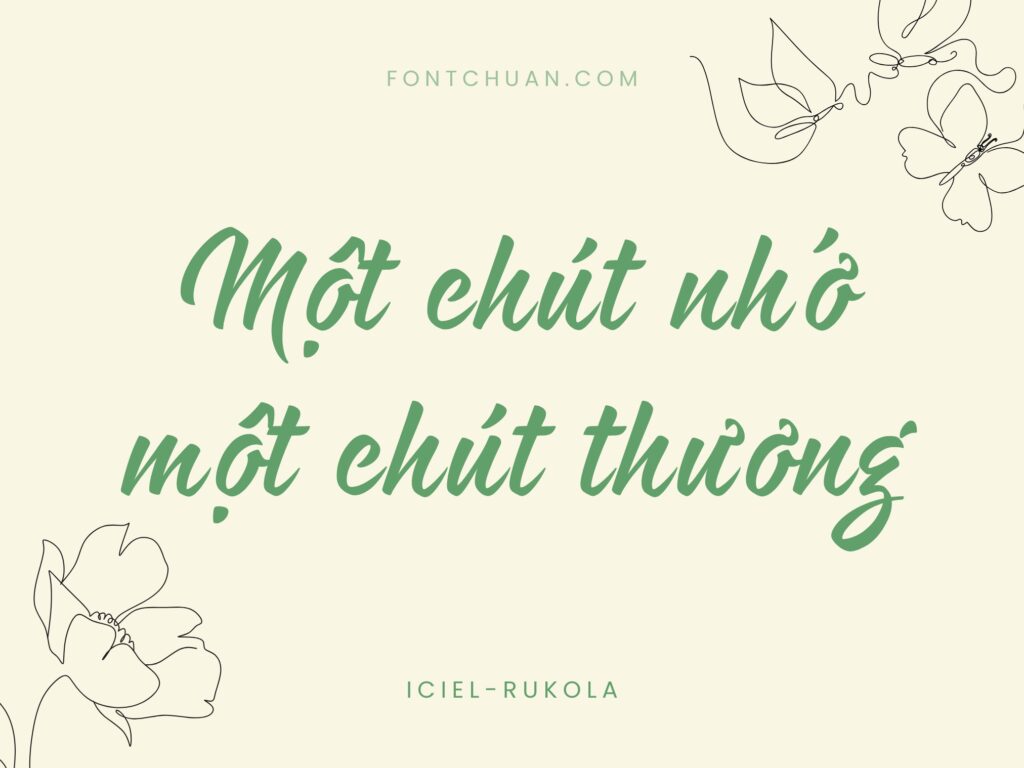
Font iCiel Rukola Việt Hóa
Rukola là một kiểu chữ viết tay thân thiện, được thiết kế bởi nhà thiết kế người Séc, Nikola Giacintová. Lấy cảm hứng từ nghệ thuật vẽ biển hiệu truyền thống, Rukola mang đến cảm giác vui tươi và năng động cho các thiết kế. Đặc biệt, Rukola đã được Việt hóa bởi iCiel, hỗ trợ tiếng Việt cùng nhiều ngôn ngữ khác, đáp ứng nhu cầu đa dạng của người dùng. Thành viên của Font Chuẩn đã sưu tầm và chia sẻ font này, giúp cộng đồng thiết kế ứng dụng dễ dàng trong các dự án của mình.
Về đặc điểm thiết kế, Rukola sở hữu các nét cọ mềm mại, uyển chuyển với độ tương phản cao, tạo nên sự nổi bật và thu hút. Font này phù hợp cho các thiết kế như logo, tiêu đề, poster, bao bì sản phẩm và các ấn phẩm truyền thông cần sự sáng tạo và cá tính. Ngoài ra, Rukola còn thích hợp cho các ngành nghề như quảng cáo, ẩm thực, thiệp cưới và spa, cùng các sự kiện đặc biệt như lễ hội, sinh nhật, Halloween và Trung thu.